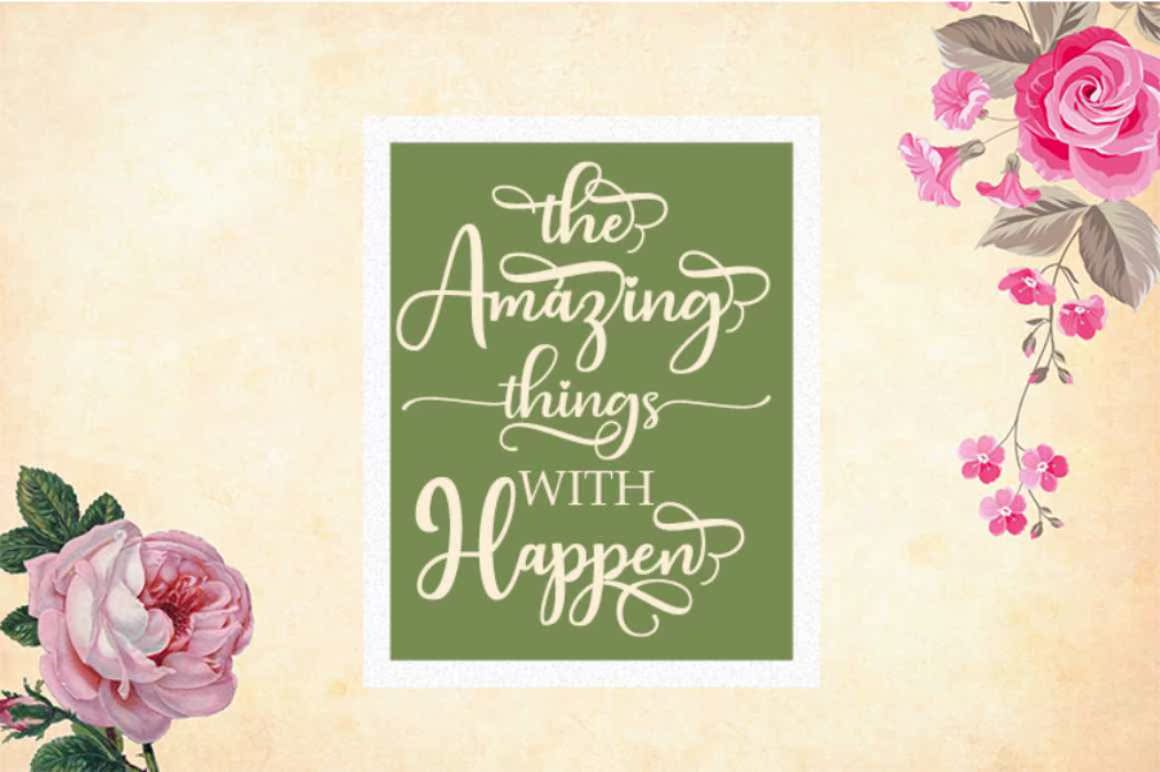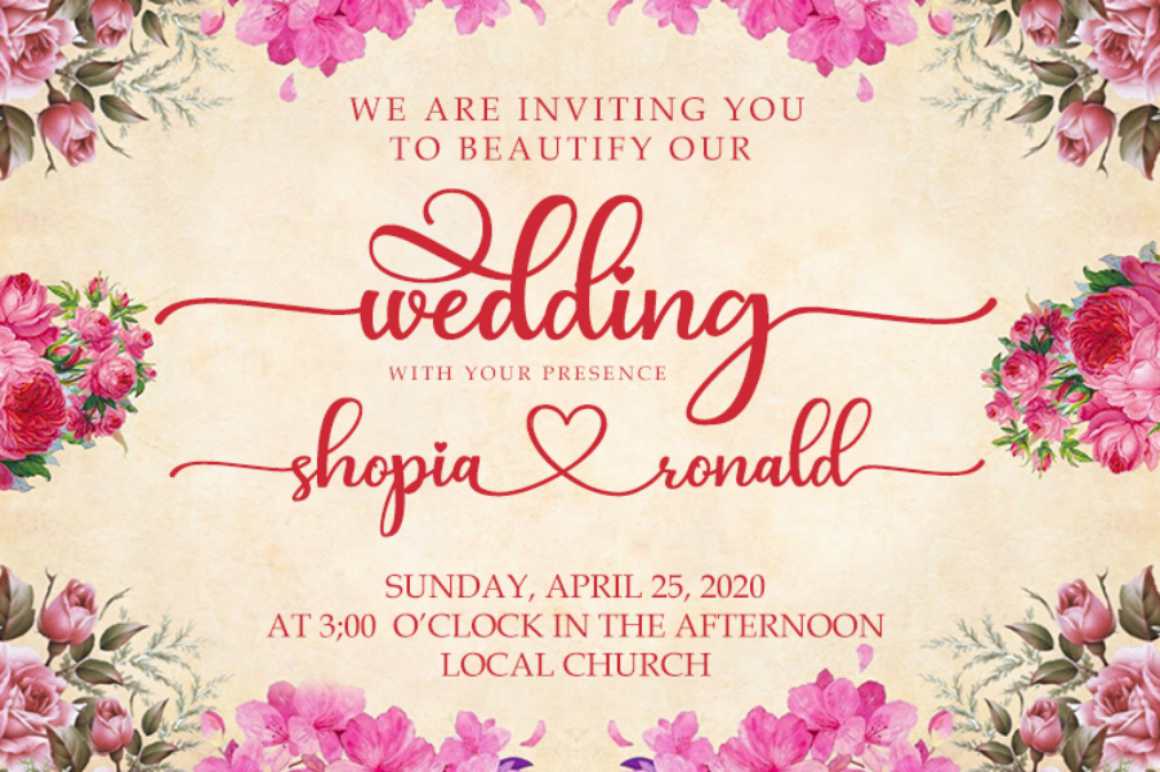
FatayahirhamiFontsarebeautifulslick脚本,适用于品牌推广、婚礼激励和其他浪漫项目。-fatayahirhami.otf(所有字母)-fatayahirhamitail.otf(开始和结束Swash.Shift“字母”=左侧Swash。“字母”=右侧Swash)-fatayahirhamiheart.otf(连接心形Swash)注意:如果购买,您将获得3个Fontfile文件。它们是“fatayahirhami”,“fatayahirhamitail”和“连接心脏的FatayaHirhami心脏”。i将其放入3个文件中,以便在开始显示清洗时使用,选择“fatayahirhamitail”。例如,您可以键入“ShopayaHirhami”,开头为wash和connecting hearts。步骤:选择“fatayahirhami”并按Shift。您将使用初始wash收到邮件。然后,选择“fatayahirhami”作为普通/常规字母。键入“hopi”。之后,选择“fatayahirhami连接心脏的心脏”,键入“a”,因此,您将获得心形图。接下来,您再次选择“fatayahirhami”输入“pap”。然后,选择“fatayahirhanitail”,输入“d”(无换档),因此,您将在洗漱结束后收到通知。您将在回顾时收到Wordsliek的报告。如果您有问题,请发邮件。Fatayahirhamifonts将避免点击适合品牌、婚礼和活动的脚本,和其他浪漫项目。-fatayahirhami.otf(allletters)-fatayahirhamitail.otf(start&endswash.Shift“letter”=左侧swash。“letter”=右侧swash)-fatayahirhamiheart.otf(connectingheartswash)注意:如果购买,您将获得3fontfiles。它们是“fatayahirhami”,“fatayahirhamitail”,和“连接心脏的FatayaHirhami Hearts”。i将其放入3个文件中,以便开始显示清洗的开始,您可以选择“fatayahirhamitail”。例如,您可以在清洗和连接心脏的开始处键入“shopiaronald”。步骤:选择“fatayahirhamitail”并按Shift键。您将使用初始清洗获得这些文件。然后,您选择“fatayahirhami”作为普通/常规字母。输入“hopi”。之后,选择“fatayahirhami连接心脏的心脏”,输入“a”,这样您将与心脏相连。接下来,您选择“fatayahirhami”作为“pap”类型。然后,选择“fatayahirhami”,输入“d”(不带换档),因此,您将在清洗结束后收到邮件。瞧,您将收到一份有关您所查看的文件的详细信息。如果您有任何问题,请发邮件。